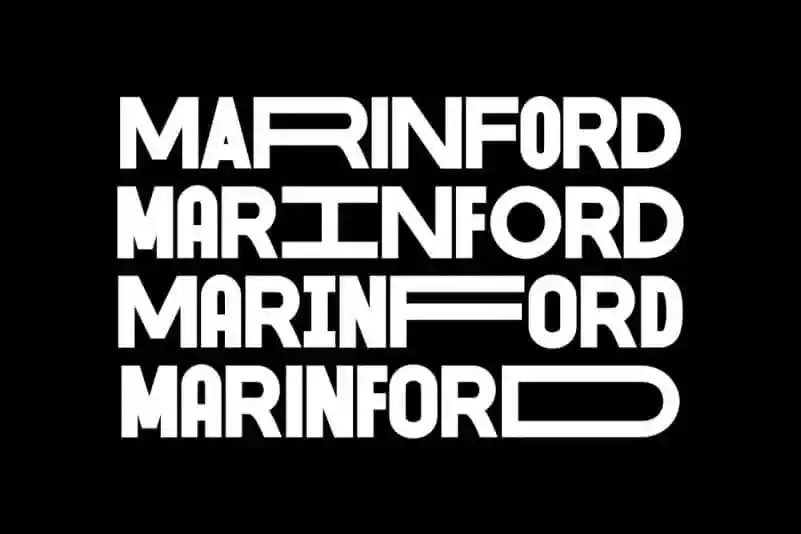
Introduzimos a Marinford Display Font, uma elegante serif sans-serif que traz beleza e sofisticação para seu projeto. Com várias ligaduras e alternativas, esta fonte moderna destaca-se entre os demais. Ela foi criada por Andika Fez, designer de 99designs, com um design único e incrível. Marinford Display é uma escolha ideal para você que busca uma mistura de elegância sofisticada com a praticidade dos caracteres sans serif. Está disponível tanto em formato de título quanto para nomes de empresa e convites casamento. É perfeitamente adaptável a diversas finalidades, como correspondência, selos, cartazes, cartão de visita, etiquetas e até mesmo para criação de selo e identificação de produtos. Seja você um designer gráfico que busca inovação em seu trabalho ou uma pessoa que deseja adicionar um toque único a seus materiais impressos, Marinford Display está aqui para dar um salto na sua produção visual.